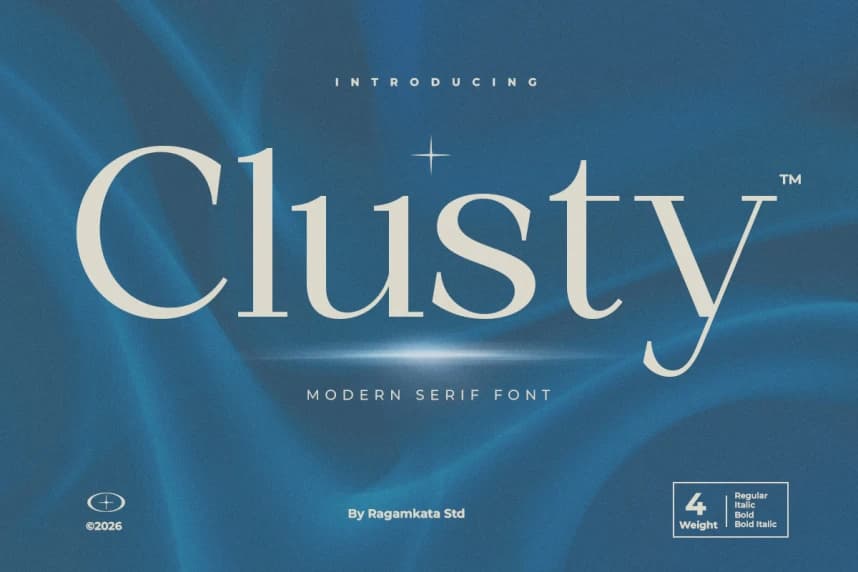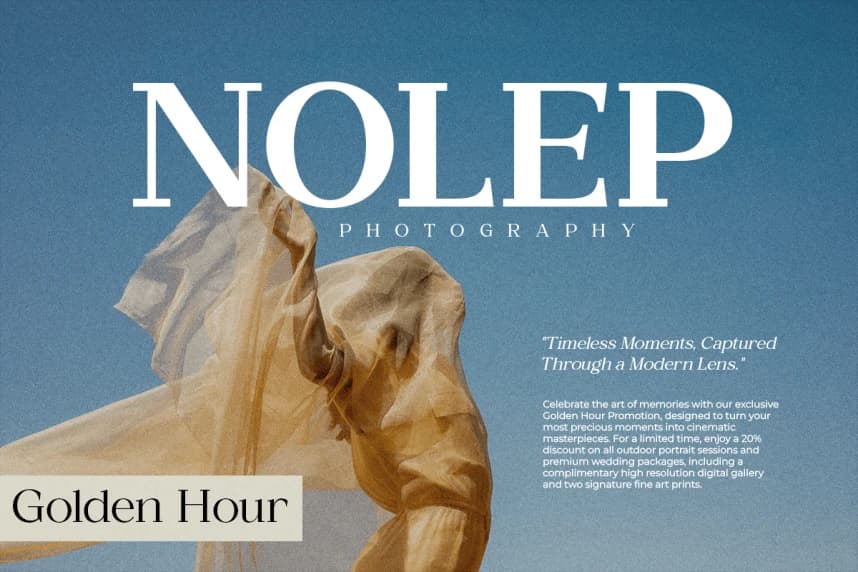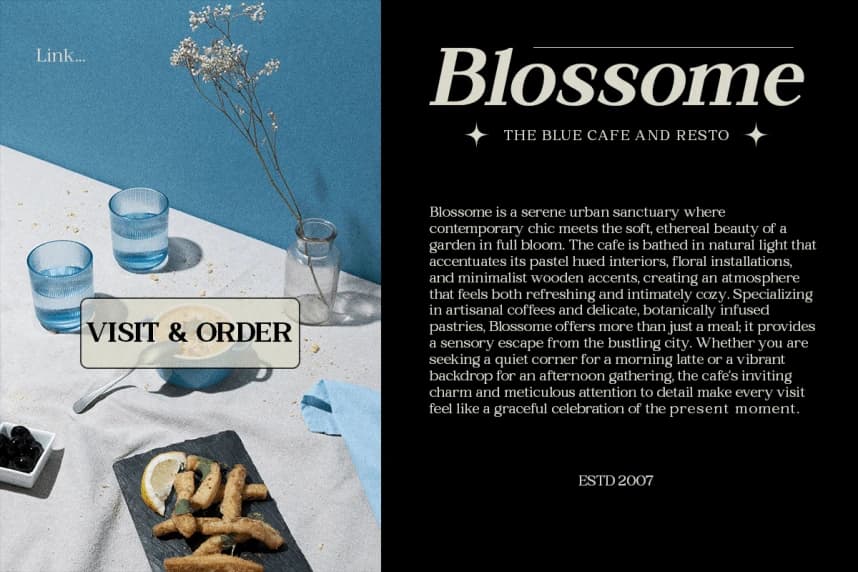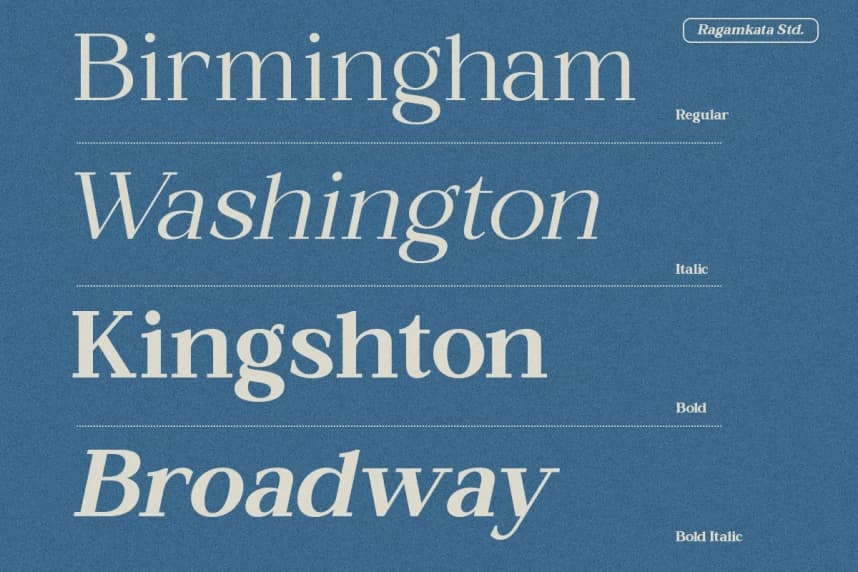
Clusty Font
Clusty Font, zarafeti yumuşak çağdaş bir dokunuşla birleştiren modern bir serif yazı tipidir. İnce kıvrımlar ve zarif harf biçimleriyle tasarlanmıştır; bu sayede her tasarıma sakin ama sofistike bir duruş kazandırır.
Clusty Font, zarafeti yumuşak çağdaş bir dokunuşla birleştiren modern bir serif yazı tipidir. İnce kıvrımlar ve zarif harf biçimleriyle tasarlanan bu yazı tipi, her tasarıma sakin ama sofistike bir duruş sağlar.